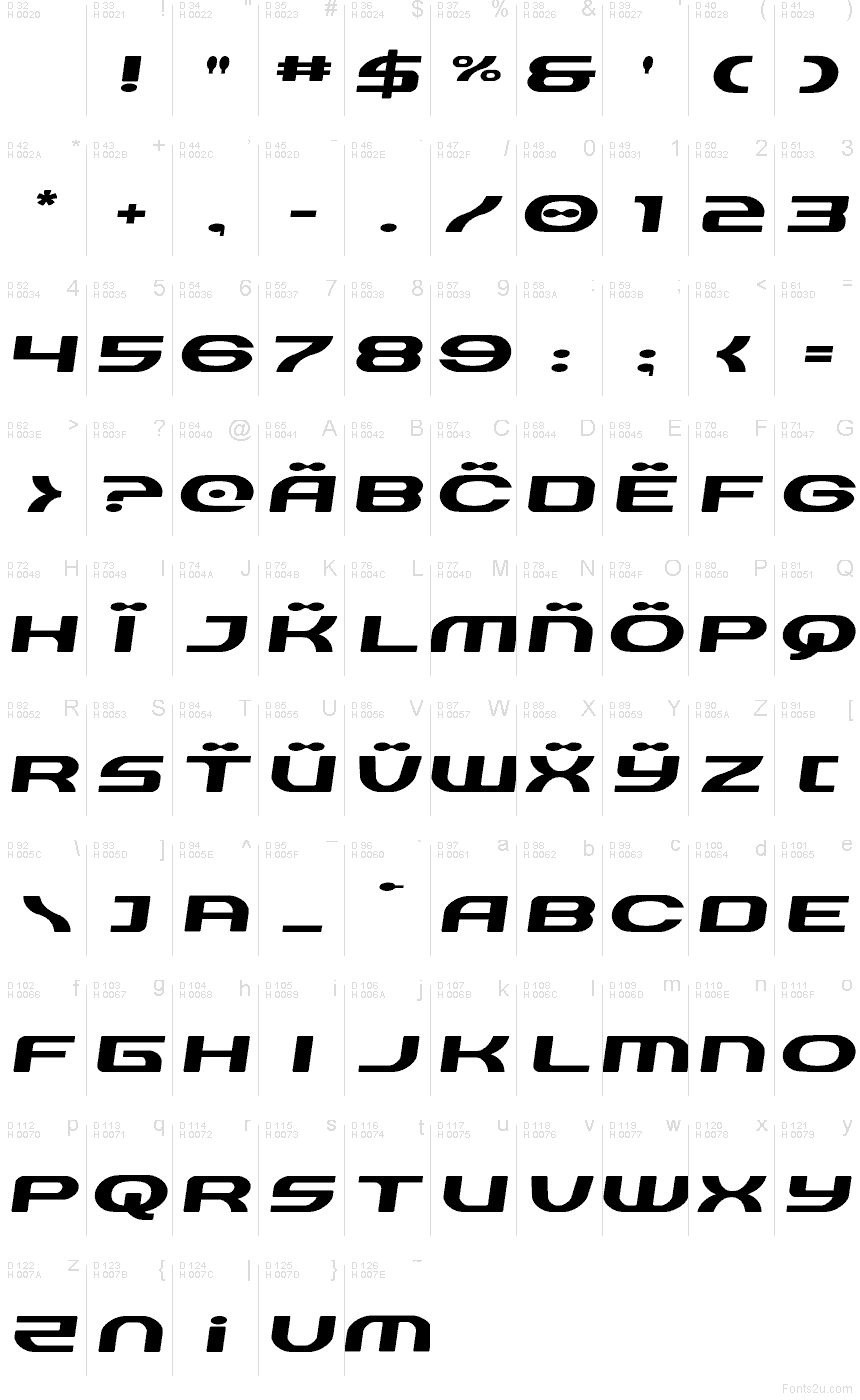
vOiture Expanded Semi-Italic par Iconian Fonts est une police d'affichage techno élargie et gratuite, dotée de caractères larges et inclinés vers l'avant ainsi que d'une silhouette élégante aux coupes nettes. Des courbes arrondies côtoient des extrémités tranchées de façon abrupte dans l'ensemble du lettrage.
L'identité visuelle automobile et les affiches de musique électronique évoquent le même sentiment de vitesse, bien que l'une paraisse conçue par ingénierie et l'autre plus théâtrale. Sa largeur marquée convient également aux interfaces de jeux vidéo et aux articles de sport, où les lettres peuvent s'intégrer dans une bande de course ou un graphisme inspiré d'un tableau de bord. Sur les visuels événementiels, les extrémités coupées peuvent rappeler des flèches, des marquages de piste et des icônes directionnelles.